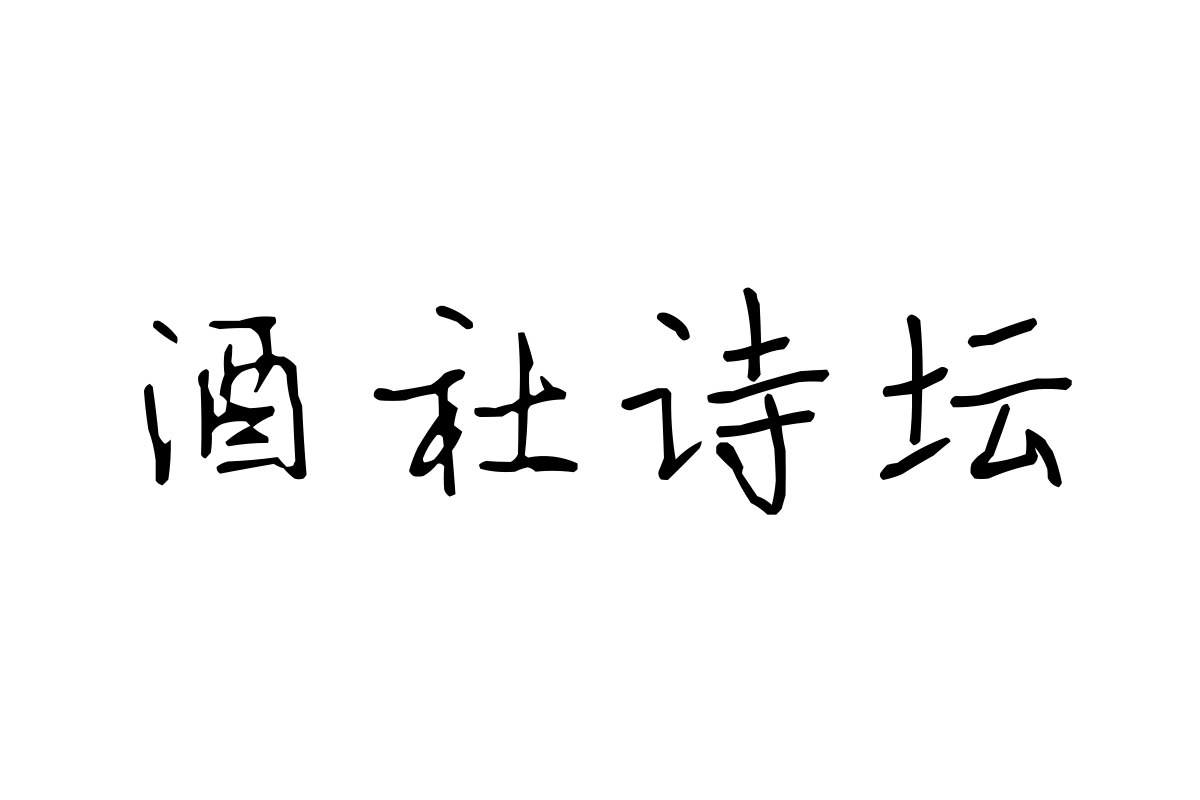
三极执子之手是一款中文书法字体,由设计师王明洋在2015年设计。这款字体具有独特的风格和韵味,适合用于书法、海报、广告等场合。
特点:
1. 字形独特:三极执子之手的字形结构独特,笔画流畅,富有美感。
2. 线条流畅:这款字体的线条流畅自然,给人一种优雅的感觉。
3. 易读性高:由于字形结构简单,笔画清晰,因此阅读起来非常方便。
4. 适用范围广:适用于各种需要书写的场合,如书法、海报、广告等。
使用场景:
1. 书法作品:适合作为书法作品的书写字体。
2. 海报设计:适合用于海报的设计,增加视觉效果。
3. 广告设计:适合用于广告设计,提升品牌形象。
4. 其他需要书写的场合:如签名、笔记等。